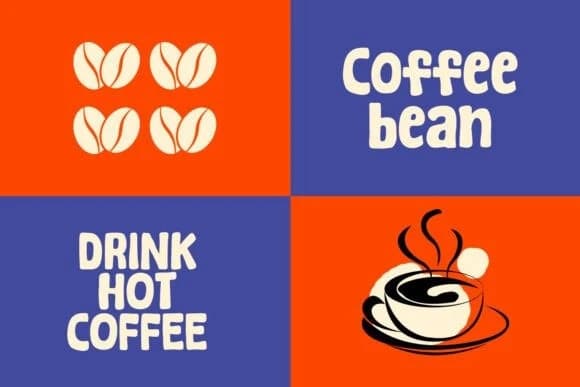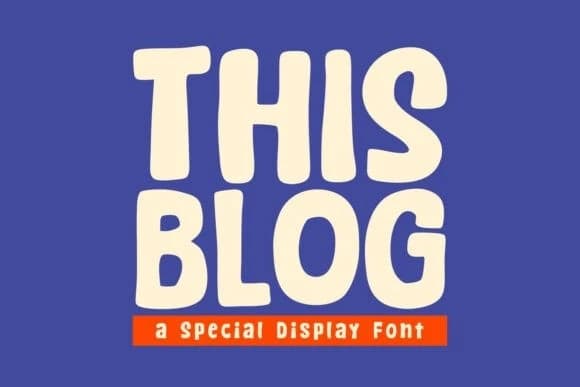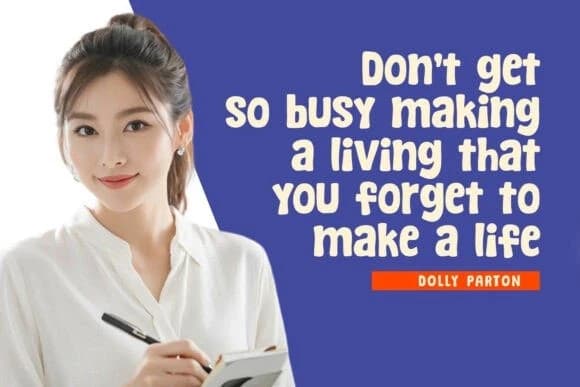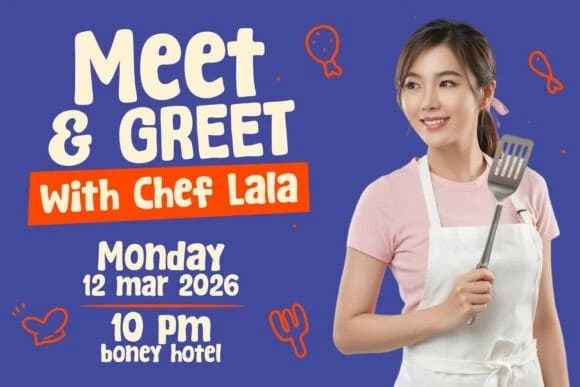
Bu Blog Display Font, posterler, logolar, dergiler, kitap kapakları, afişler ve daha pek çok şey için mükemmel olan modern ve sevimli bir gösterim yazı tipidir. Bu harika fontu elde edin ve onu güzel tasarımlar yaratmak için kullanın. Son derece geniş bir proje yelpazesine kolayca uyum sağlar.
Bu Blog Display Font, posterler, logolar, dergiler, kitap kapakları, afişler ve daha pek çok şey için mükemmel, modern ve sevimli bir gösterim yazı tipidir! Bu harika fontu edinin ve güzel tasarımlar yaratmak için kullanın. İnanılmaz geniş bir proje yelpazesine kolayca uyum sağlar.